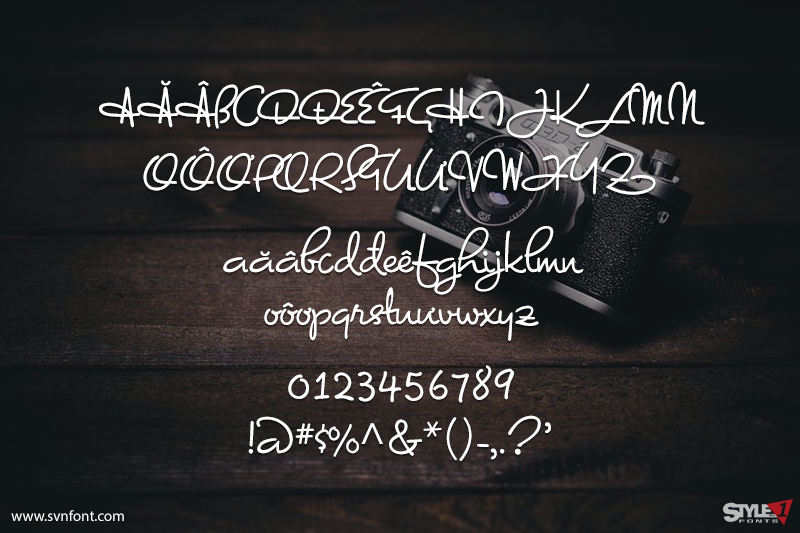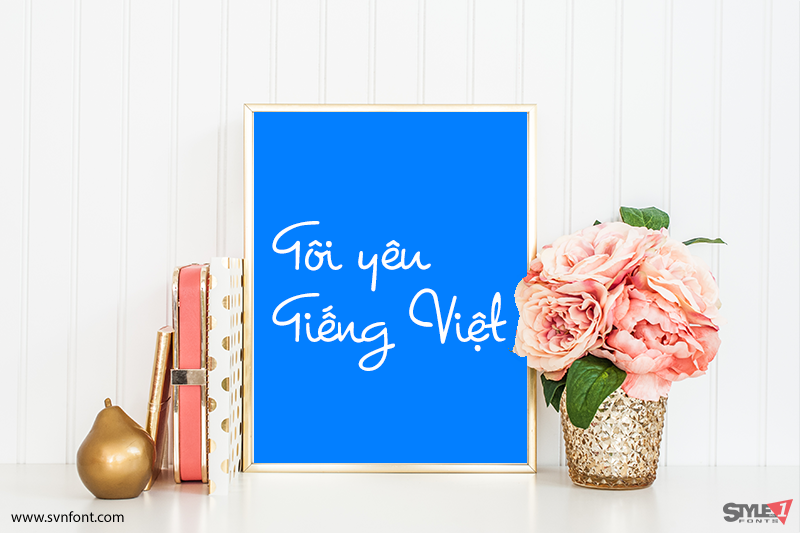
Dominique – font chữ viết tay hiện đại và đẹp mắt. Font thích hợp cho thiết kế: thiệp cưới, trang trí, bìa sách, nhãn hiệu, logo, banner…
Nhà thiết kế: Canada Type
Nhà phát hành: Canada Type